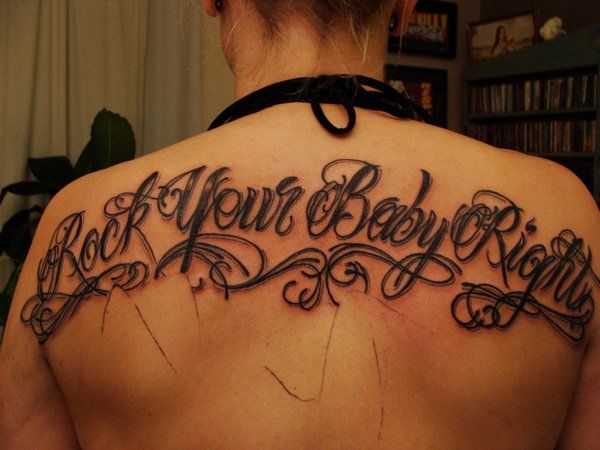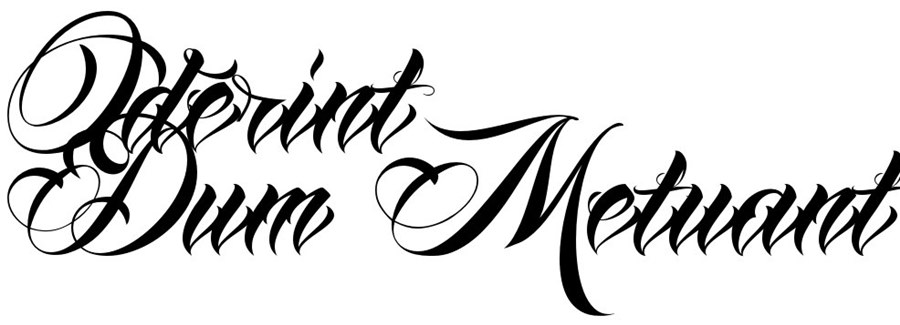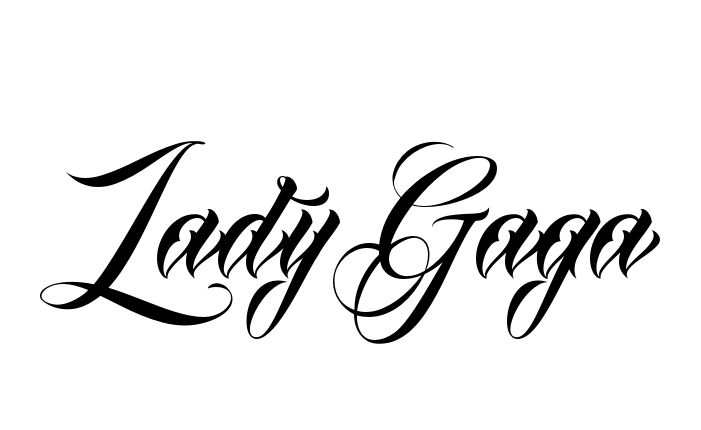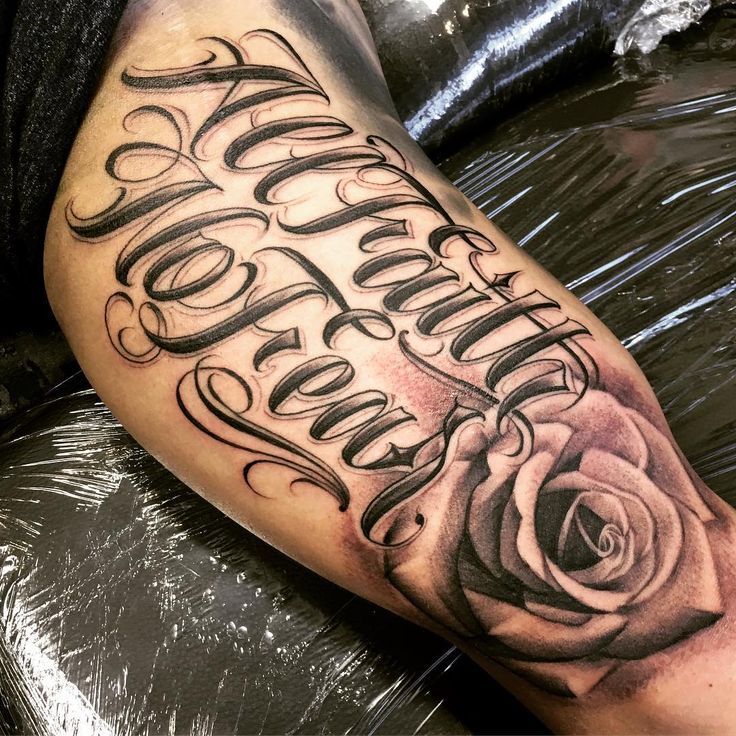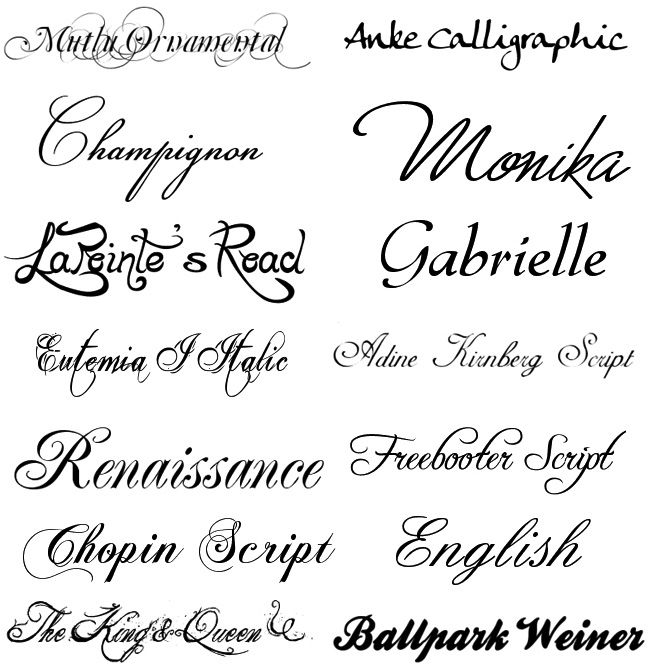
Как сделать надпись красивым шрифтом онлайн
Наверное, каждый из нас имеет свой любимый ресурс для создания изображений. И знает одну единственную проблему, с которой приходится мириться – отсутствие поддержки латиницы. Если бы нам были доступны все красивые шрифты онлайн сервисов, то, уверяю вас, наши статьи были бы украшены не только красивыми картинками, но и имели бы красивые надписи и заголовки текстов.
Предлагаю для тестирования сервис, в котором можно легко и быстро сделать надпись красивым шрифтом онлайн. Сервис Translate-tattoo вообще-то предназначен для подбора шрифта и создания надписи для татуировок… Но нам он тоже может пригодиться. Тем более, что работать в нем можно бесплатно и без регистрации.
Что понравилось:
- Выбор русских шрифтов – есть из чего выбрать!
- Несмотря на то, что сервис предназначен для тех, кто делает тату, многими шрифтами может воспользоваться и веб мастер
- Есть, хотя и ограниченная, возможность изменить размер и цвет надписи
- Можно быстро разобраться и за пару минут сделать надпись
Чего не хватило:
- Ограниченная возможность изменения цвета, размера
- Отсутствие вариантов начертания текста
- Явно прослеживается узнаваемость шрифта для татуировок, хотя есть поле для творчества…
Так как плюсов оказалось больше, то я рекомендую сервис своим читателям!
Как работать
- Перейдите на сервис Translate-tattoo
- Напишите свой текст.
- Рекомендую пропустить выбор размера и цвета шрифта. А вот русский язык нужно выбрать сразу.
- Спуститесь ниже по странице и посмотрите все представленные варианты шрифтов. Их даже можно все протестировать – нажмите на выбранном шрифте кнопку “Применить шрифт”.
- Поднимитесь в строку введения текста и посмотрите результат.
- А вот теперь можно изменить размер и цвет шрифта, так как один и тот же размер не будет одинаково отображаться на всех шрифтах.
Пары минут хватает, чтобы освоиться и сделать надпись красивым шрифтом. По крайней мере, это удобно, не сложно, и в некоторых случаях может здорово пригодиться. Украшайте свои картинки на сайтах, в блогах и в социальных сетях красивыми надписями и заголовками!
Онлайн шрифты для татуировок прописью.
Ink Hunter — виртуальная примерка татуировок перед походом в тату-салонДля тех, кто решил нанести на тело татуировку, наиболее серьезной проблемой является выбор рисунка или надписи. Ведь трудно создать тату надпись так, чтобы не пожалеть об этом в течение всей жизни. Трудно однако очень даже возможно, для этого изначально следует рассмотреть абсолютно все варианты, взвесить преимущества и недостатки, а также понять, что именно вы хотите видеть на себе каждый день.
Во многих случаях, когда человек вроде бы уже определился с выбором надписи, проблемой становится тату шрифт, которым будет сделана татуировка.
На нашем сайте есть функция “подбор тату шрифта онлайн “, благодаря которой вы можете ввести желаемую фразу и поэкспериментировать с различными стилями и шрифтами.
Для того, чтобы смысл надписи совпадал бы со стилем, следует понять, что одна черточку, наклон буквы или размер слова может повлиять на восприятие смысла.
Если для татуировки вы выбрали длинную надпись или даже целое предложение, то советуем подобрать более компактные виды шрифтов, буквы в котором наносятся без наклона или же с небольшим наклоном.
Генератор шрифтов для татуировки к Вашим услугам!
Вы можете выбрать любой из шрифтов представленных в нашем сервисе!
| Если Вы решили сделать себе татуировку надпись и хотите, чтобы в ней не было ошибок в написании и переводе, то Вы можете заказать перевод у профессиональных переводчиков на нашем сервисе. Также Вы можете подобрать шрифт для своей тату надписи, воспользовавшись нашим сервисом подбора шрифтов. | ||
Одним из самых распространенных стилей тату-индустрии является нанесение какого-либо текста для выполнения татуировки в итоге. Выбор текста – вопрос непростой, но еще более сложным будет выбор самого шрифта. Учитывая целое море вариантов, а также индивидуальный подход мастера к каждому, можно долго рассуждать о конкретных типах тату.
Стиль шрифта
Как выбрать шрифт для тату? Первым делом, если Вы определились с текстом, нужно подобрать соответствующее оформление.